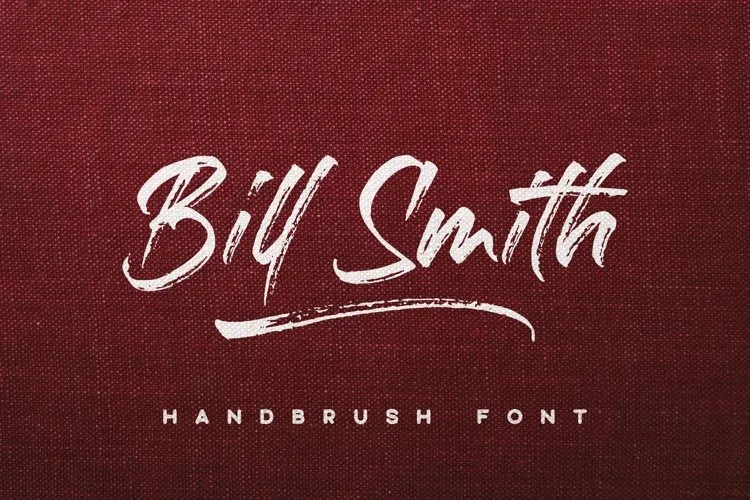
Bill Smith Font – Download Grátis
Esta fonte é perfeitamente adequada para quem procura uma opção de tipo à mão escrita com textura de pincel. Ideal para diversas aplicações gráficas, como design de marca, cartas de casamento, anúncios, cartões de visita, avisos, papelaria, logotipos, embalagens e muitos outros formatos. Perfeita tanto para criar um visual elegante e sofisticado quanto para adicionar uma textura única e personalizada a seus projetos. Seja você designer gráfico ou criador de conteúdo, a fonte Bill Smith é um ativo valioso para aumentar o impacto de seu design.